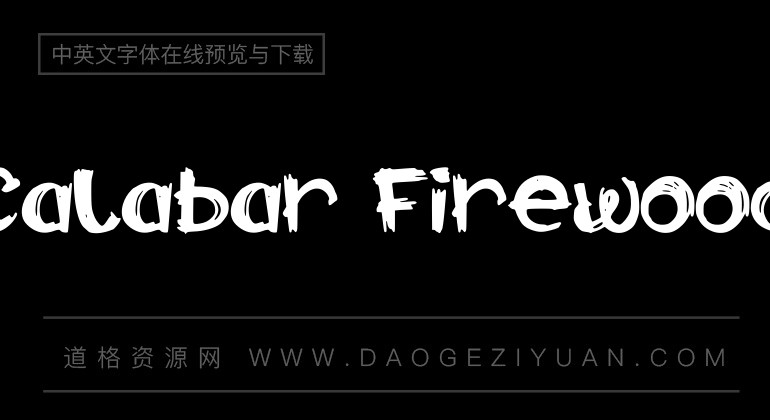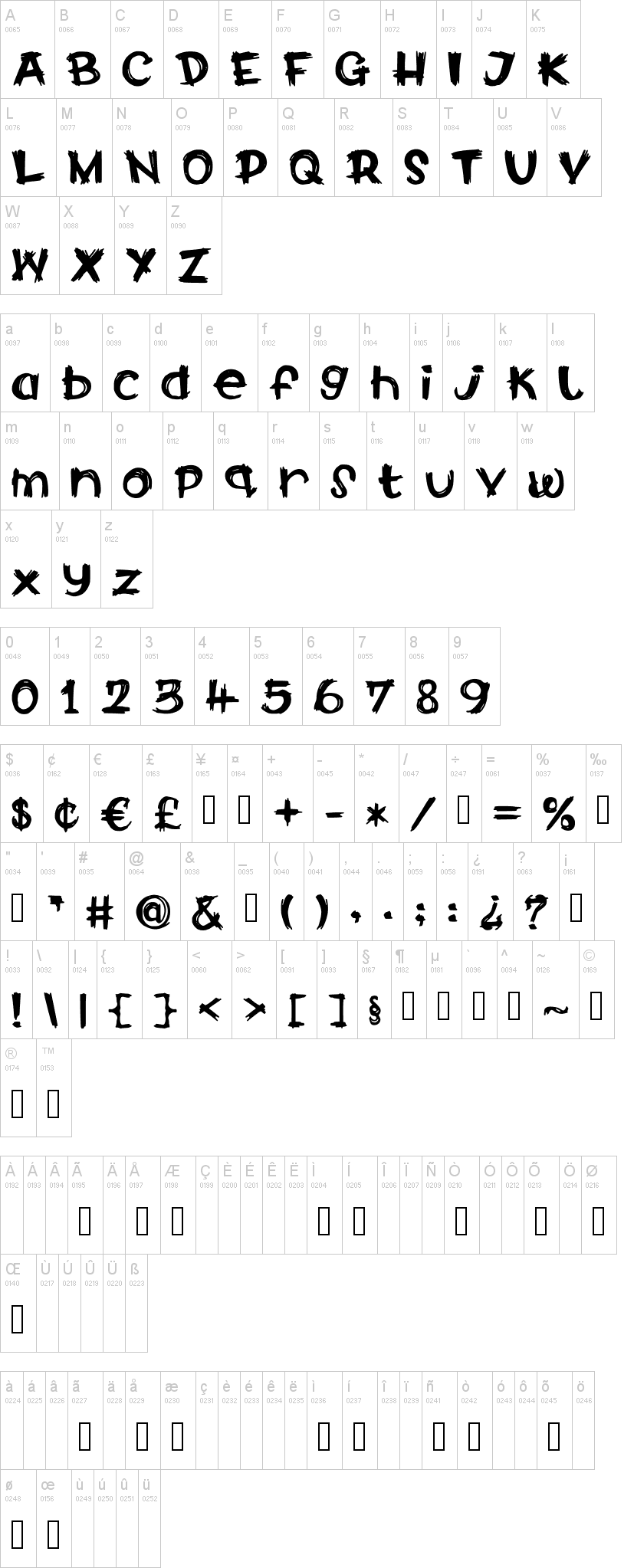
Calabar Firewood 是一款折衷字体,它源自非洲文化,融入了传统的西非纹样和形状,带有浓郁的色彩,充满活力和激情。它适用于标题、标签和标语,可以在网站、印刷品、商标、海报、T恤等上使用。Calabar Firewood 的字体特点是它的特殊的轮廓,它的字母有着圆滑的曲线,给人一种温暖而精致的感觉。它的元素也很细腻,可以用来制作华丽的印刷品和海报。内容介绍
Calabar Firewood是一款非常不错的手写艺术字体,具有很好的视觉感,适合于文化类的宣传设计、商业类品牌的广告和产品包装设计以及个性化文字排版等较多场景。